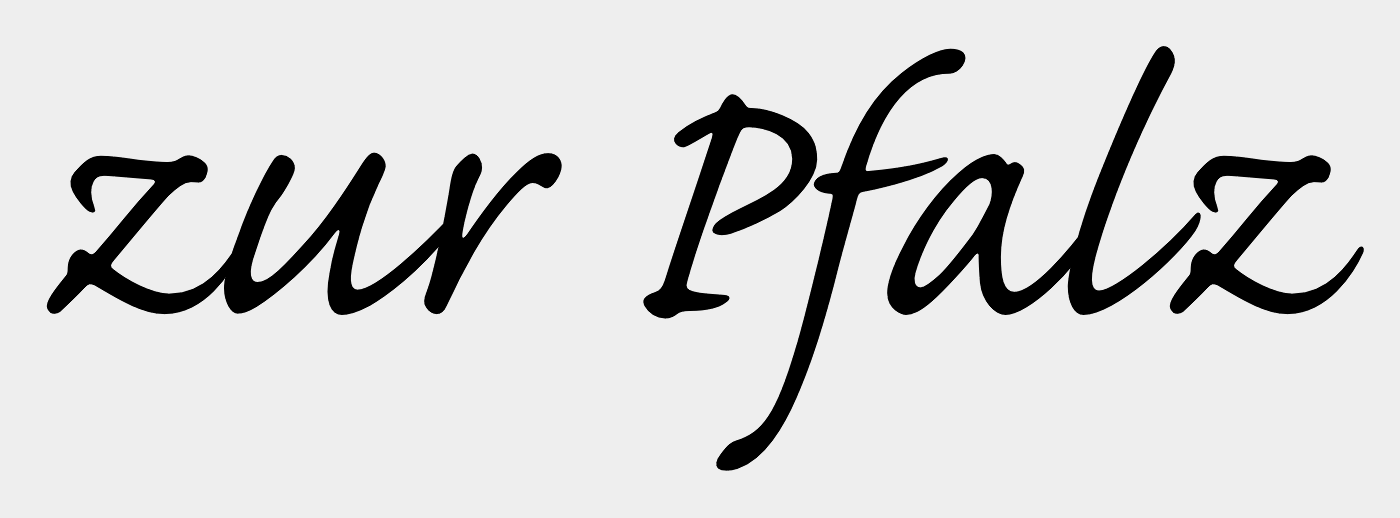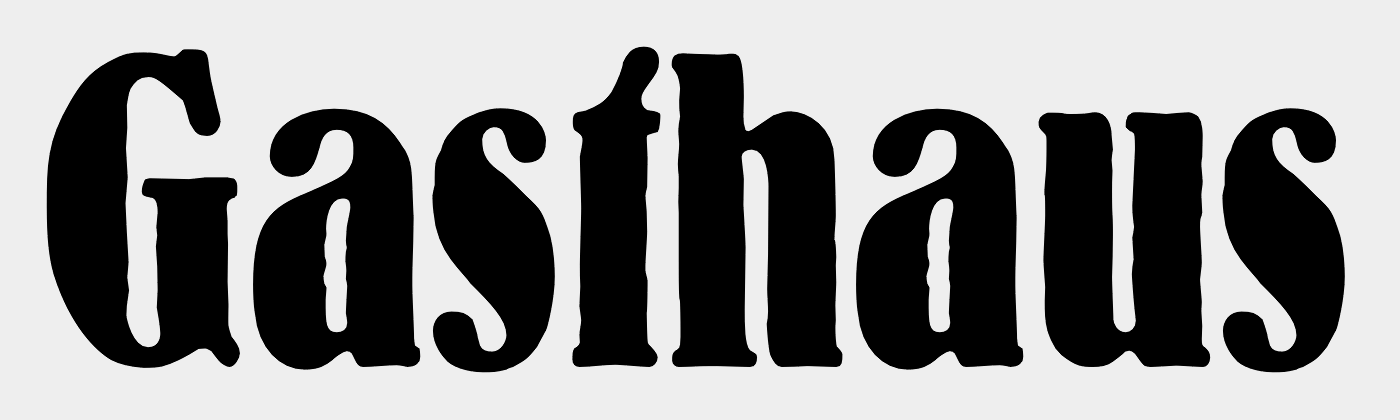
Suche Schriftarten von "Gasthaus zur Pfalz"
kennt jemand die Schriftarten von "Gasthaus" und "zur Pfalz".
Bei dafont bin ich nicht fündig geworden.
Ähnliche Schriftarten würden mir auch schon helfen.
... das Wort Gasthaus war zu Bleisatzzeiten die Schrift "Bernhard-Antiqua schmalfett.
Gießerei war die Bauersche Gießerei in Frankfurt/Main. Der Erstguß erfolgte 1914.
Schriftentwerfer war Lucian Bernhardt.
Zur zweiten Schrift kann ich derzeit leider nichts beitragen.